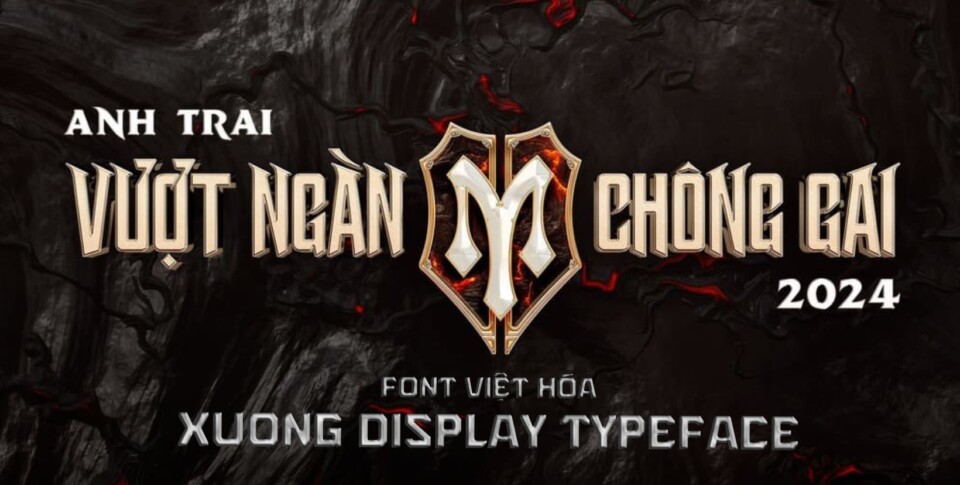
Chào mừng các bạn yêu thích thiết kế đồ họa quay trở lại. Trong năm 2024, chương trình truyền hình thực tế đình đám đã tạo nên một cơn sốt không chỉ về âm nhạc mà còn về phong cách thẩm mỹ độc đáo. Điểm nhấn ấn tượng nhất chính là bộ Font Việt hóa Xuong Display Typeface – Anh trai vượt ngàn chông gai 2024. Đây là mẫu Font Chữ mang đậm hơi thở nghệ thuật đương đại, kết hợp hoàn hảo giữa nét truyền thống và tinh thần mạnh mẽ của những “anh tài”. Việc sử dụng bộ phông này sẽ giúp các dự án của bạn trở nên chuyên nghiệp và thu hút hơn bao giờ hết.
Đặc điểm nổi bật của Font Việt hóa Xuong Display Typeface – Anh trai vượt ngàn chông gai 2024
Thiết kế góc cạnh và cá tính
Bộ font này gây ấn tượng mạnh nhờ cấu trúc hình khối vững chãi, các đường nét được cắt gọt tinh tế tạo cảm giác vừa gai góc vừa uyển chuyển. Nó phản ánh đúng tinh thần vượt qua khó khăn, thử thách để tỏa sáng. Xuong Display cực kỳ phù hợp cho các tiêu đề lớn, banner quảng cáo hoặc bìa album âm nhạc.
Khả năng hiển thị tiếng Việt hoàn hảo
Điểm quan trọng nhất là bộ font đã được Việt hóa chỉn chu, hỗ trợ đầy đủ các dấu câu mà không bị lỗi hiển thị. Điều này giúp các bạn học sinh và nhà thiết kế dễ dàng sáng tạo nội dung truyền thông mà vẫn giữ được tính thẩm mỹ nguyên bản của tác giả.
Ứng dụng Font Việt hóa Xuong Display Typeface – Anh trai vượt ngàn chông gai 2024 vào thực tế
Các bạn có thể sử dụng bộ chữ này để thiết kế poster cổ động, làm phụ đề video hoặc tạo các ấn phẩm trường học đầy năng động. Sự kết hợp giữa màu sắc rực rỡ và kiểu chữ mạnh mẽ sẽ tạo nên hiệu ứng thị giác tuyệt vời. Hy vọng bộ font này sẽ là nguồn cảm hứng mới cho các bạn. Hãy tải ngay Font Miễn Phí, Font Việt Hóa, Font Việt hóa Xuong Display Typeface – Anh trai vượt ngàn chông gai 2024 để bắt đầu hành trình sáng tạo của riêng mình nhé.